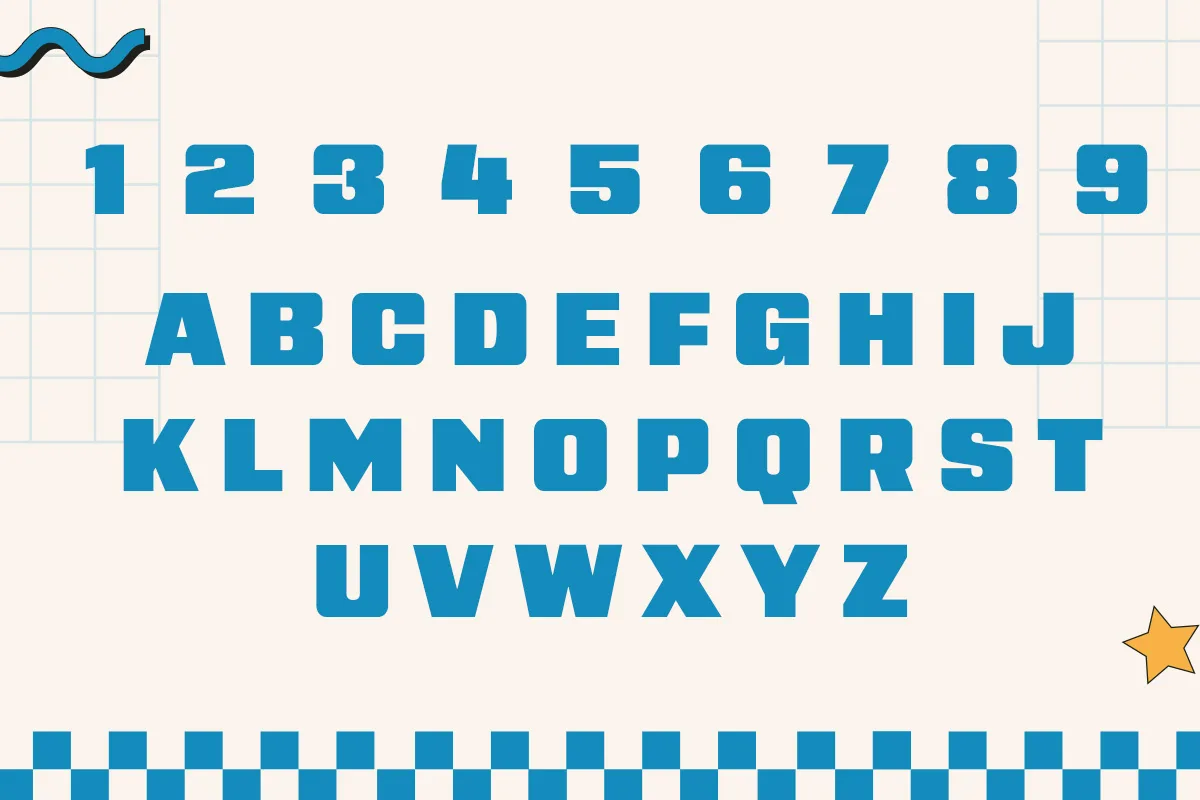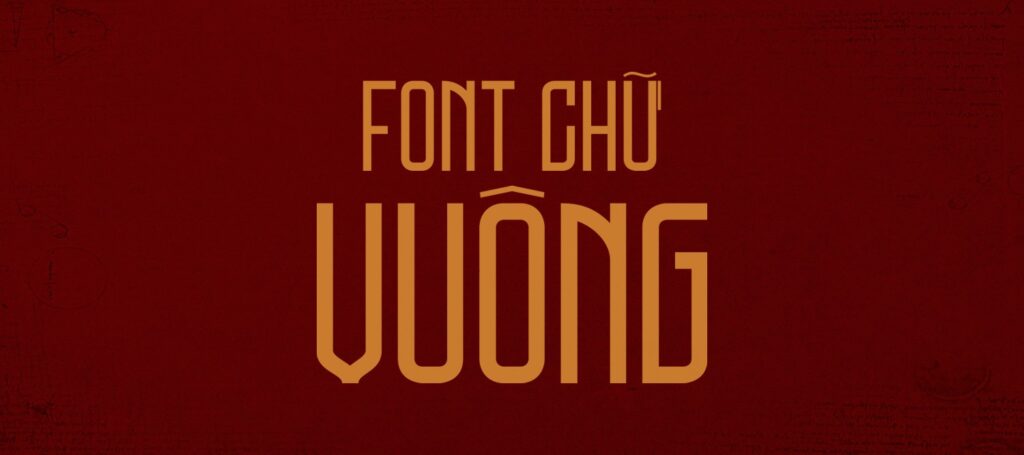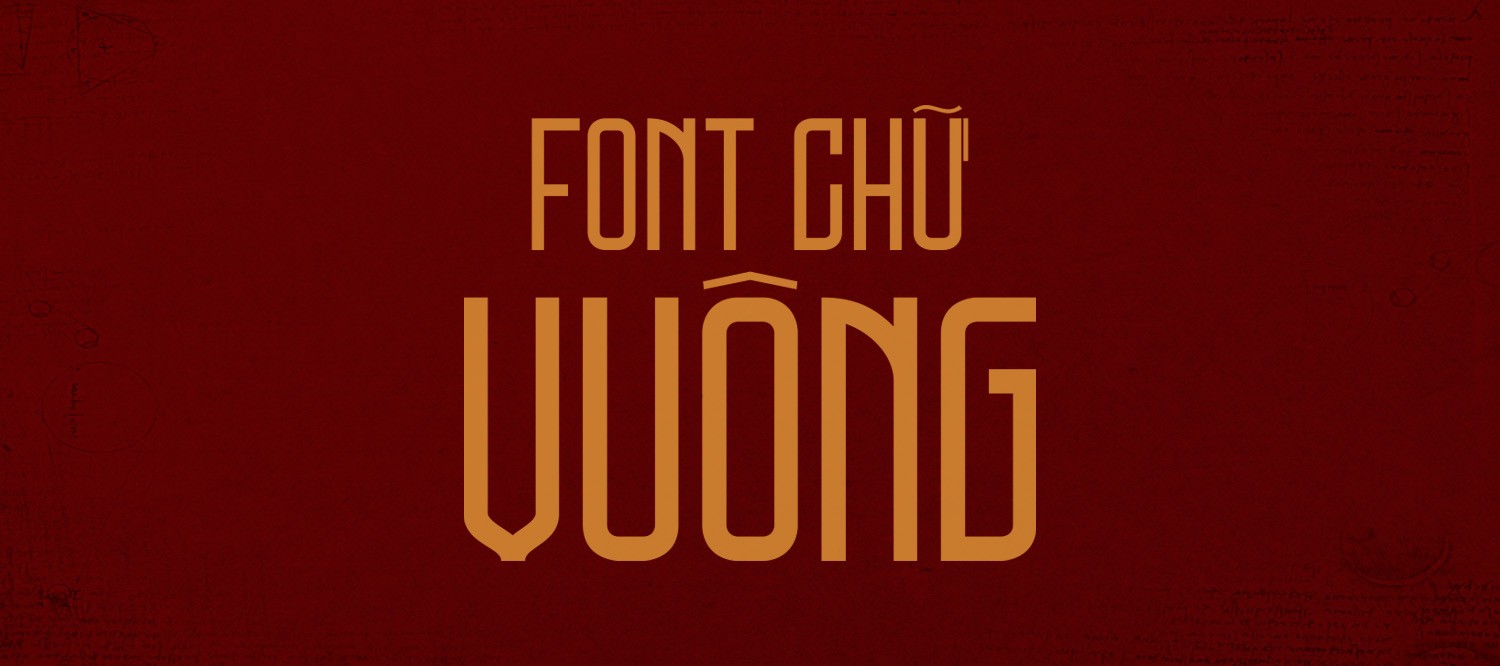
font chữ vuông
Font chữ vuông là font có góc vuông 90 độ, nét thẳng mang phong cách geometric, công nghiệp được sử dụng rộng rãi trong thiết kế bao bì sản phẩm công nghệ, túi giấy thương hiệu tech và in ấn poster hiện đại. Font chữ vuông việt hóa với đặc điểm mạnh mẽ, cứng cáp tạo cảm giác chuyên nghiệp, industrial.
Font chữ vuông là gì?
Font chữ vuông (square font) là font có các góc chữ vuông góc (90 độ) hoặc gần vuông góc, tạo cảm giác cứng cáp, mạnh mẽ, công nghiệp. Khác với font bo tròn (rounded) mềm mại, font vuông mang năng lượng masculine, technical.
Phân loại font chữ vuông:
• Font vuông hoàn toàn: Mọi góc đều 90 độ, không bo tròn – tạo cảm giác rất cứng, industrial (ví dụ: Orbitron, Rajdhani).
• Font vuông bo góc nhẹ: Góc vuông nhưng có bo tròn nhẹ (1-2px) để dễ đọc hơn – vẫn mạnh mẽ nhưng không quá cứng (ví dụ: Chakra Petch).
• Font chữ triện vuông: Font display với hình khối vuông, thường dùng cho tiêu đề lớn, logo.
Cảm giác mà font vuông tạo ra:
• Mạnh mẽ, cứng cáp: Góc vuông tạo cảm giác quyết đoán, mạnh mẽ, không mềm yếu.
• Công nghệ, hiện đại: Font vuông gợi liên tưởng đến chip điện tử, circuit board, digital.
• Công nghiệp, mechanical: Phù hợp ngành sản xuất, ô tô, máy móc, công cụ.
• Nam tính, bold: Font vuông thường được cảm nhận là masculine hơn rounded.
Chakra Petch
Vuông công nghệ Thái Lan, futuristic Bao bì điện tử, gaming, tech gadget
Orbitron
Vuông sci-fi, geometric future Logo công ty tech, poster sự kiện innovation
Rajdhani
Vuông modern Ấn Độ, sharp Bao bì công nghiệp, nhãn máy móc
Share Tech
Vuông tech monospace, digital Sản phẩm software, developer tool
Electrolize
Vuông electronic, circuit board Bao bì linh kiện điện tử, PCB
Exo 2
Vuông geometric tech, 18 weights Catalogue công nghệ, brochure startup
Saira
Vuông semi-condensed, 9 weights Poster industrial, standee machinery
Quantico
Vuông military, tactical Bao bì outdoor gear, tactical equipment
Lưu ý: Font chữ vuông đặc biệt phù hợp cho tiêu đề, logo – nên hạn chế dùng cho body text dài vì khó đọc.
Ứng dụng font vuông trong bao bì
Font chữ vuông với phong cách mạnh mẽ được ưa chuộng trong các ngành:
• Phù hợp sản phẩm tech, công nghệ: Font vuông gợi liên tưởng đến chip, circuit, digital – lý tưởng cho điện tử, software, gadget.
• Tạo cảm giác industrial, chắc chắn: Góc vuông tạo impression sản phẩm bền, chắc, đáng tin – phù hợp công cụ, máy móc.
• Nam tính, bold: Font vuông thường được chọn cho sản phẩm nam, thể thao, outdoor, automotive.
• Futuristic, innovation: Font vuông tạo cảm giác tương lai, đổi mới – phù hợp startup innovation, AI, robotics.
Font chữ vuông xuất hiện trong nhiều sản phẩm in ấn:
• Bao bì sản phẩm điện tử: smartphone, laptop, tablet, accessories tech.
• Túi giấy công ty công nghệ: startup AI, robotics, semiconductor, chip design.
• Logo công ty công nghiệp: sản xuất, cơ khí, ô tô, máy móc.
Font chữ vuông xu hướng chắc chắn
1. Font vuông có nên dùng cho body text không?
Không nên. Font vuông khó đọc khi dùng cho văn bản dài vì góc cạnh gây mỏi mắt. Nên dùng font vuông cho logo, tiêu đề, số – body text nên dùng sans-serif thông thường.
2. Font vuông nào dễ đọc nhất?
Chakra Petch và Exo 2 dễ đọc nhất vì có nhiều weight và spacing tốt. Orbitron và Electrolize quá stylized, chỉ nên dùng cho display/heading.
3. Nên dùng font vuông cho sản phẩm nào?
Font vuông phù hợp: điện tử, công nghệ, công nghiệp, gaming, automotive, outdoor gear, công cụ, machinery. Sẽ không phù hợp: mỹ phẩm, thời trang nữ, kids, organic, wellness.